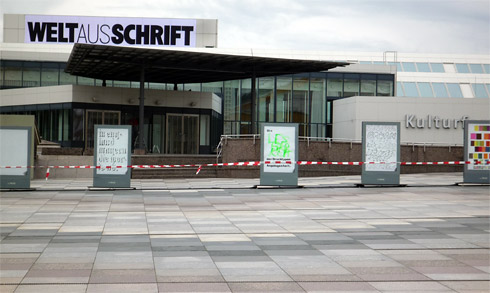
Morgen um 19 Uhr öffnet die große Ausstellung Welt aus Schrift im Berliner Kulturforum ihr Pforten, Untertitel: »Das 20. Jahrhundert in Europa und den USA«. Keine andere Epoche hat einen solchen Reichtum von Schriftformen hervorgebracht, und noch nie war Schrift in einer vergleichbar medialen Vielfalt präsent: im Internet, in Informations-, Werbe- und Buchmedien, im öffentlichen Raum, in der Mode, in Fotografie, Film und Kunst. In chronologischen Schritten wirft die Ausstellung ihre Schlaglichter auf die typografischen Revolutionen des 20. Jahrhunderts, die Interaktion von Schrift und Bild und die vielfältigen Wechselwirkungen zwischen freier und angewandter Kunst.
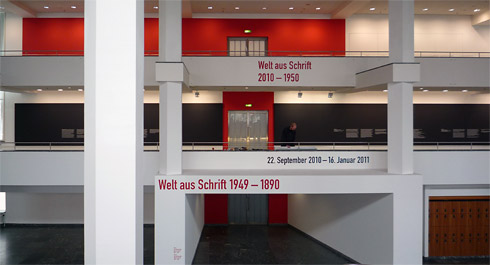
Für die Kunstbibliothek der Staatlichen Museen zu Berlin ist die „Welt aus Schrift“ seit mehr als einem Jahrhundert ein zentraler Sammlungsschwerpunkt. Ihre Bestände zur Schriftgeschichte der letzten hundert Jahre reichen von den Pressendrucken der englischen Buchkunstbewegung im ausgehenden 19. Jahrhundert, den Schriftkreationen des Jugendstils über die frühe Moderne, den Dadaismus und die Propagandamedien der 30er und 40er Jahre bis hin zu Pop, Fluxus, Concept Art und Digital Art. Neben angewandten Arbeiten der freien Kunst gilt das Sammelinteresse vor allem den Entwicklungen des Grafikdesign in den Alltagsmedien wie Zeitschrift, Buch, Zeitung, Plattencover, Inserat und Plakat und darüber hinaus den Beispielen des modernen Kommunikationsdesigns.
Zum breiten Spektrum grafischer Gestaltungen gehören auch solche, die eine Wiederentdeckung verdient haben wie jene, die heute bereits als Klassiker gefeiert werden. Meisterwerke wie das Monumentalplakat zur Fritz Langs »Metropolis« von 1927 sind Unikate von Weltrang. In der Ausstellung »Welt aus Schrift« wird dieses universale Medienarchiv erstmals in seinem ganzen Umfang für die Öffentlichkeit erlebbar.
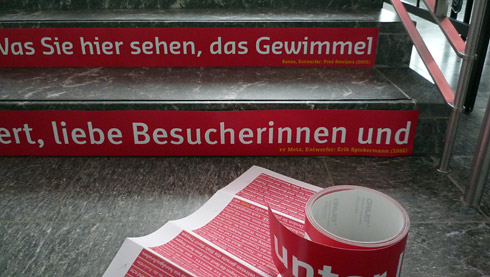
Die Ausstellung in den Hallen am Kulturforum (Potsdamer Platz) beschreibt auf über 1000 qm mit fast 600 Exponaten eine Reise durch die Zeit in Etappen, die jeweils zwanzig Jahre umfassen: den Aufbruch in neue Gestaltungen als Reaktion auf den drohenden Qualitätsverlust im Zeitalter industrieller Druckherstellung (1890 – 1909), die typografischen Innovationen der Moderne (1910 – 1929), Einflüsse des Art Déco und die Instrumentalisierung der Schrift als politische Botschaft (1930 – 1949), die Nachkriegsmoderne zwischen swiss style und new bauhaus; die Auflösung der Grenzen zwischen Schrift und Bildender Kunst in Pop Art, Konkreter und Visueller Poesie (1950 – 1969), die Dekonstruktion der Schrift zwischen Konzeptkunst und Postmoderne (1970 – 1989) und schließlich die digitale Renaissance der Schrift als Universalmedium einer globalisierten Welt (1990 – 2009).
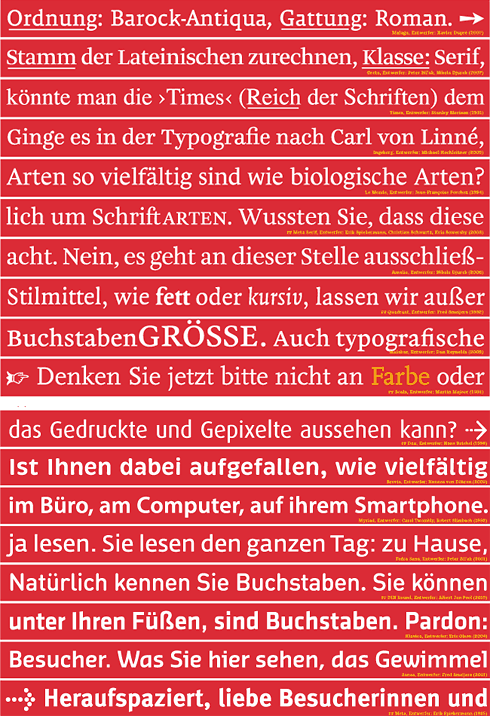
Die Ausstellung erstreckt sich über 3 Etagen, die durch ein Treppenhaus mit 6 Treppen verbunden sind. Auf Vorschlag der Kuratorin Dr. Anita Kühnel und des Ausstellungsgestalters Bernard Stein durfte FontShop die verbindenden Treppen mt einer typografischen Installation zur Ausstellungsfläche umfunktionieren. Mehr als 60 Stufen erzählen eine Geschichte der Schriftvielfalt, die von unten nach oben zu lesen ist. Jeder der 6 Treppen widmet sich einer Schriftklasse, so wie sie aus FontBook und FontShuffle bekannt sind: Sans, Serif, Slab, Script, Display und Blackletter. Die obige Abbildung zeigt die Beschriftung der ersten beiden Treppen, die gerade im Kulturforum beklebt werden (Produktion: Heyer Grafische Dienstleistungen). Morgen veröffentliche ich hier im Fontblog die gesamte Treppengeschichte, erzählt mit 60 Schriften, als PDF.
kurzer Zwischenruf:
Ist hier vom 20. Jahrhundert in Verbindung mit dem Internet die Rede?
Oder wird das 21. Jahrhundert gemeint sein?!
Die Ausstellung widmet sich der Schriftkultur des 20. Jahrhunderts (mit wenigen Exponaten jünger als 1999), aus der Perspektive des 21. Jahrhunderts.